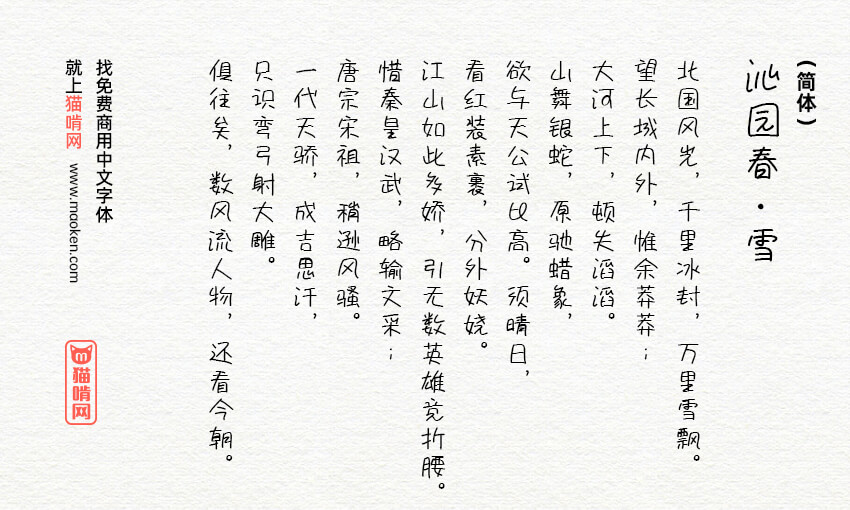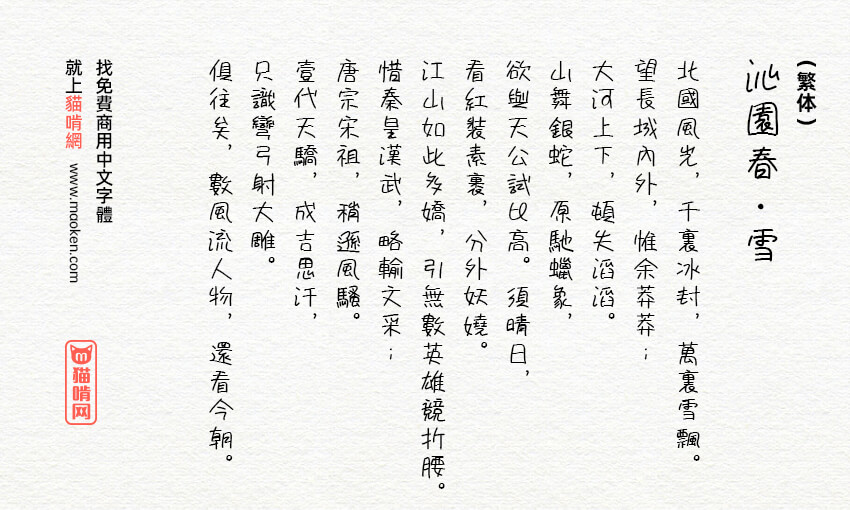
851手写杂书体:原子笔字形风格的手写字体
字体名称: 851手写杂书体 (851手書き雑フォント)PS中字体名称:851tegakizatsu
字体版本:Version 0.883(最终更新:2016/05/24)收录汉字:简体★★★★★ / 繁体★★★★★
今天分享这款手写字型 《851手写杂书体》是日本设计师手写的一款字体,很像是一般人用原子笔书写一般。不过值得推荐的是,这一款手写字体包含了中文字相对来说是比较完整的,这点比较意外,所以使用起来还是真香的!